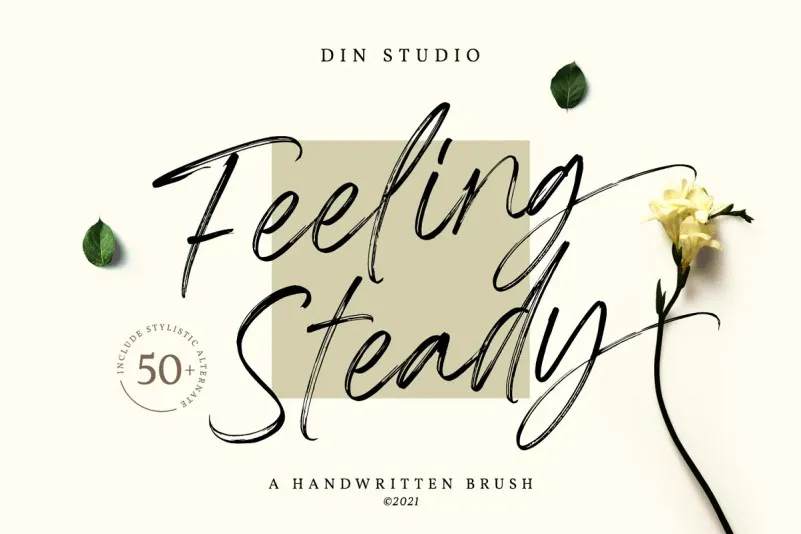
A Feeling Steady Font é uma tipografia textura feita com estilo contemporâneo por Din Studio. Ela transmite um charmoso e autêntico tom relaxado, perfeitamente adequada para enriquecer suas criações de design. É especialmente ótima para banners de redes sociais, posts e anúncios, citações impressas em camisetas, embalagens ou como superposição de texto moderna sobre qualquer imagem de fundo. Inspirar sua audiência, clientes ou convidados com o encanto da elegância é um dos benefícios desta fonte escrita a mão. Perfect para adicionar uma sensação natural às suas criações visuais.